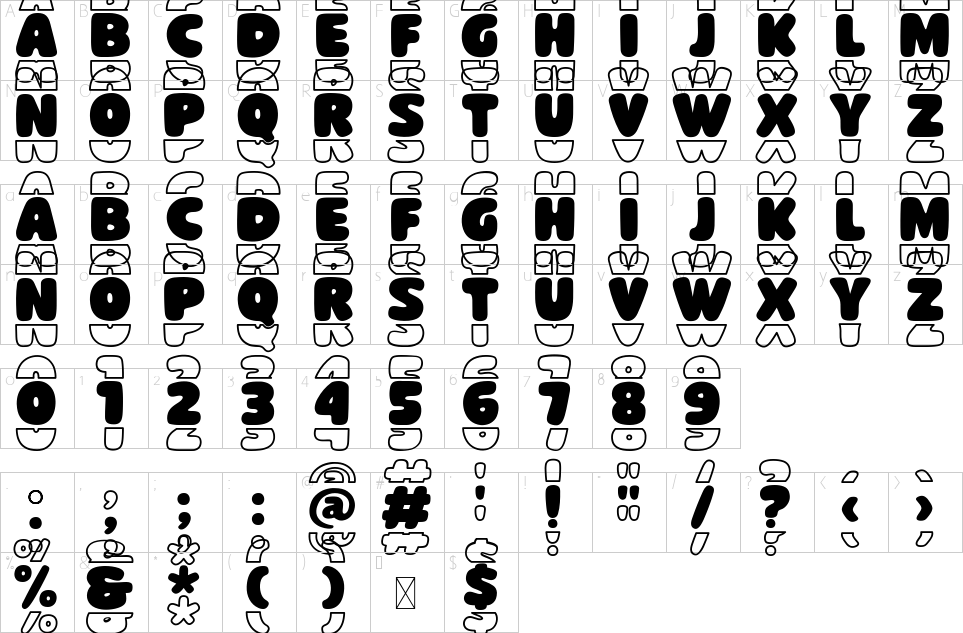
Descubra a alegria e a diversão com Jollyfun Font. Esta elegante e leve fonte foi criada por jimtype studio e é ideal para adicionar um toque alegre a qualquer projeto gráfico. Sua simplicidade e charme a tornam um recurso indispensável para designers e criativos que buscam uma fonte alegre para complementar seus trabalhos. A Jollyfun Font é perfeita para adicionar um toque descontraído a aplicativos de design, como cartazes, materiais de marketing e até mesmo para textos em documentos pessoais. Com mais de 860 downloads, Jollyfun Font é uma fonte de confiança para quem procura uma fonte divertida e alegre para personalizar seus projetos de design.